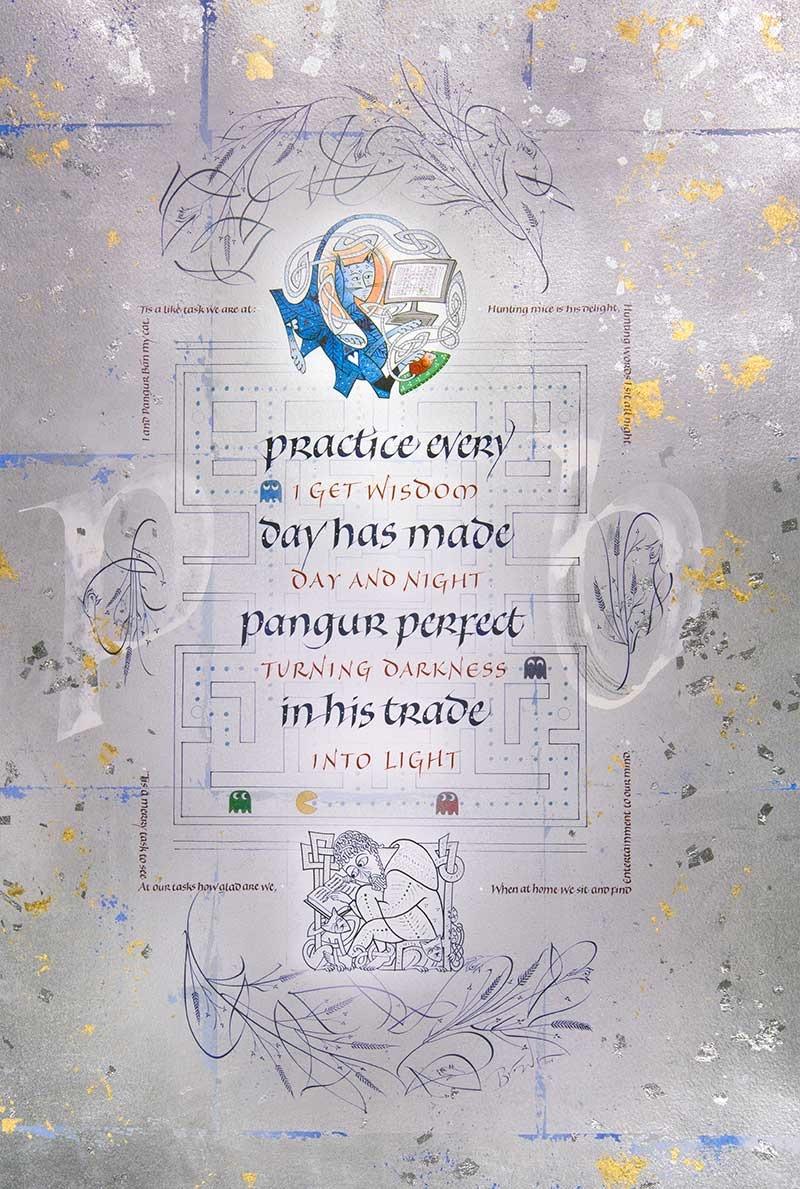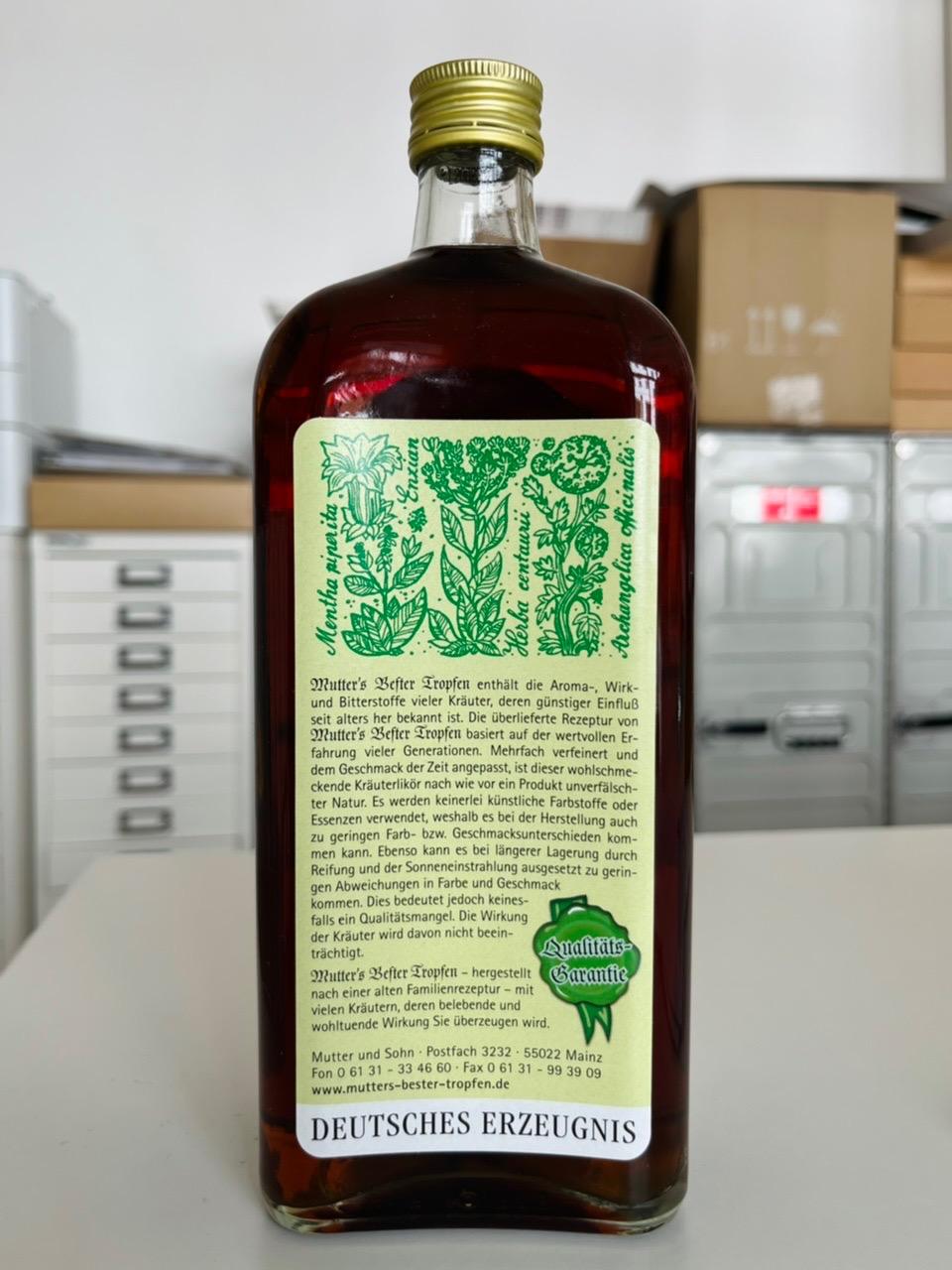
Wo es gerade so gut passt:
Olympische Spiele München 1972 Otl Aicher und das Design
@Sebastian Nagel Im Beitrag kommt auch ein junger Art Director Rolf Müller zu Wort. Den durften wir beide ja noch kennenlernen …
(Man beachte, wie viel da nebenbei geraucht und auch Alkohol getrunken wird … andere Zeiten.)
Den Beitrag spiele ich immer wieder mal unseren Praktikanten vor, um zu zeigen wie man vor dem totalen Computer-Einsatz Grafikdesign gemacht hat (Tisch, Schere, Tonpapier, Zigarette) :-)
Rolf Müller: eins der besten Seminare an der FH (für mich) ... Ein konkretes Projekt von A bis Z, unheimlich viel Input in den Entwicklungsbesprechungen, aber immer auf Augenhöhe vermittelt.
Sein konzeptioneller und semantischer Ansatz war schon beeindruckend. (…) Ich erinnere mich noch gut, wie er sagte, dass sie für die Spiele auch einen politischen Auftrag bekommen hätten. Sie dürften alles machen, nur eine Farbkombination müsse unbedingt vermieden werden: Rot / Weiß / Schwarz.
Auf YouTube hat sich auch ein Designer mal mit beschäftigt:
Mal ein Hoch auf die tollen interaktiven Infografiken zu COVID-19 bei Zeit.de, insbesondere dieser hier:
In anderen Ländern sucht man so etwas oder eine interaktive Landkarte mit detaillierten Informationen vergeblich …
Es gibt so Bildideen, die sind so naheliegend, dass man sich fragt, warum man selbst nicht längst darauf gekommen ist …
ja, zu lange getragene Masken sind Virenschleudern ... ;-)
und Vorsicht! Bei Fehlbedienung kann das alles ansteckend sein!
Da ja auch Design, wie andere Moden, immer wieder in Schleifen auf uns zu kommen scheint, hier ein Video zum Wochenstart, das vielleicht etwas Farbe in den ansonsten unlustigen Alltag bringen mag.
Aaah, Pete Beard, immer wieder toll! :nicken:
Denis Brown hat sowas ähnliches schon gemacht, bzw setzt er moderne Technik etc. in klassisch irischer Tradition in Szene:
Triggerwarnung: Er arbeitet bei seinen Plakaten viel mit Farbverläufen und Glow-Effekten wie wir sie von Photoshop und InDesign kennen und vermeiden … er macht das aber komplett analog (das ist dann wieder etwas beeindruckend).
Die Rotis lief mir erst kürzlich wieder über den Weg - kess gemischt mit einer Gebrochenen. :nicken:
Du trinkst das aber nicht?! :aschehaupt: